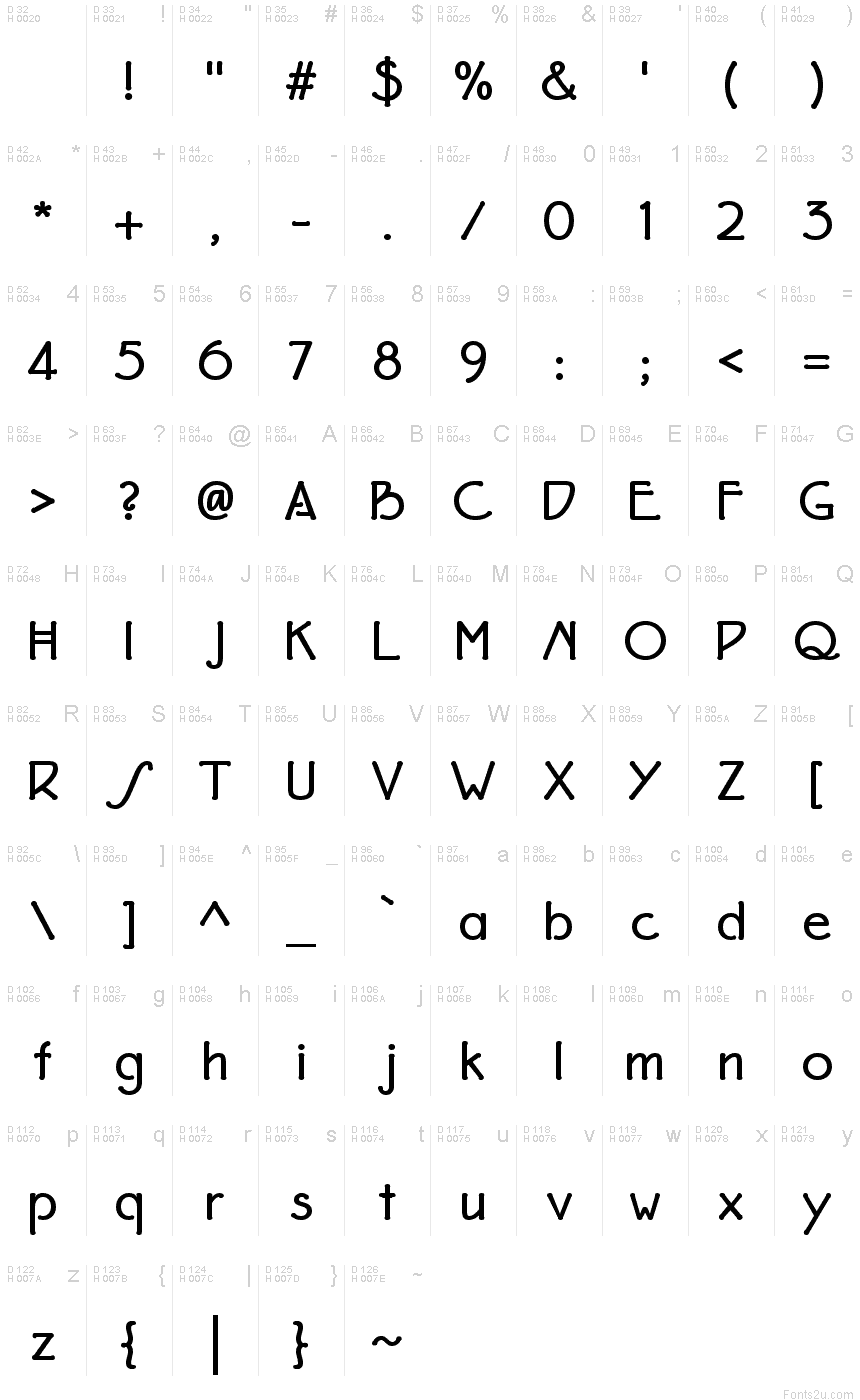
EaglefeatherFormalBold
Eaglefeather Formal Bold to darmowy krój displayowy w stylu retro o pewnym, wyrazistym, „tuszowym” ciężarze i lekko nieoczywistym rytmie. Jego masywne znaki sprawiają wrażenie, jakby zostały odbite na papierze, a miękkie krzywizny i ciasne odstępy nadają mu przyjazny, a nie sztywny charakter. Całość przywodzi na myśl połączenie dawnych szyldów sklepowych z estetyką wysłużonej maszyny do pisania.
Dzięki Eaglefeather Formal Bold uzyskasz wyraziste efekty na plakatach, w menu, na okładkach książek, w logotypach, na etykietach produktów, ulotkach i nagłówkach w mediach społecznościowych. Ten darmowy font najlepiej sprawdza się w większych rozmiarach, gdzie jego śmiałe kształty mogą w pełni wybrzmieć – jeśli wiersz wydaje się zbyt gęsty, spróbuj nieco zwiększyć światło między literami. W tekście głównym połącz go z czystym, geometrycznym krojem bezszeryfowym, aby zachować retro klimat bez utraty czytelności.